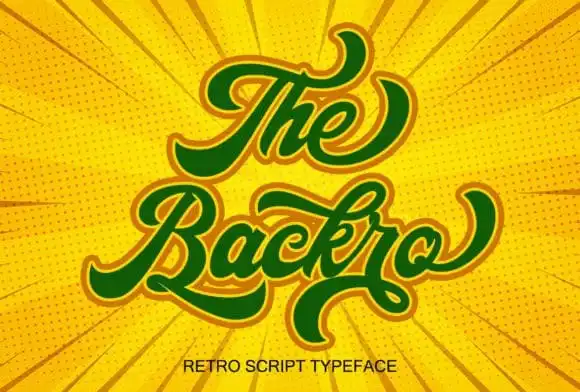
The Backro Calligraphy Font – Download Grátis
A fonte The Backro Calligraphy Font é uma elegante escolha para quem busca uma graça natural nas suas criações digitais. Desenhada com a ajuda de uma caneta-pen de ponta larga, esta fonte gótica apresenta linhas suaves e gráficos impecáveis. O estilo variável do baseline, alongado linha e alternativas estilizadas fazem dela um elemento inovador para designers que buscam dar vida aos seus projetos. Perfeita tanto para aplicar em design de sites quanto em editoriais de jornal ou qualquer outro projeto onde deseja destacar o texto com uma aparência única, a The Backro Calligraphy Font é perfeitamente adaptada à sua necessidade. Com seu estilo distintivo e eterno, esta fonte é um verdadeiro amor, criando designs que cativam e conquistam, fazendo-o a escolha ideal para quem busca destaque em seus projetos digitais.